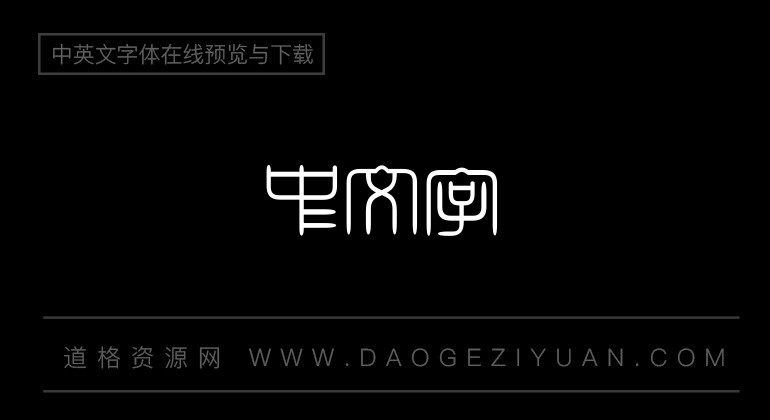
超世纪细角篆体繁
超世纪细角篆体繁(Super Century Fine Corner Seal Script)是一款繁体中文字体,由超世纪字体设计研究室设计。字体灵感来源于篆刻体,极具中国特色,是一款精致、优雅的繁体中文字体。它融合了古典的篆书笔画,拥有自然的笔画结构,字形细腻,曲线优美,极具艺术感,让人眼前一亮。
超世纪细角篆体繁是一款非常不错的手写艺术字体,具有很好的视觉感,适合于文化类的宣传设计、商业类品牌的广告和产品包装设计以及个性化文字排版等较多场景。